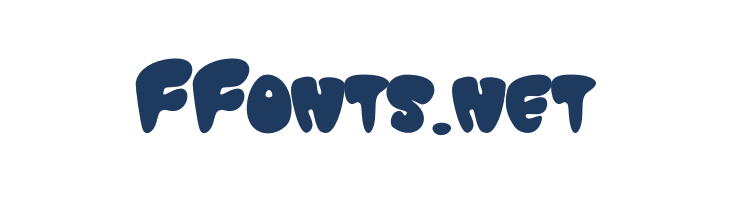
GroovyBalloon Font
Fonts by Laura
| النمط العام | Playful, Fun, Whimsical |
| مشاريع مقترحة | Ideal for children's books, party invitations, playful branding, and eye-catching posters. |